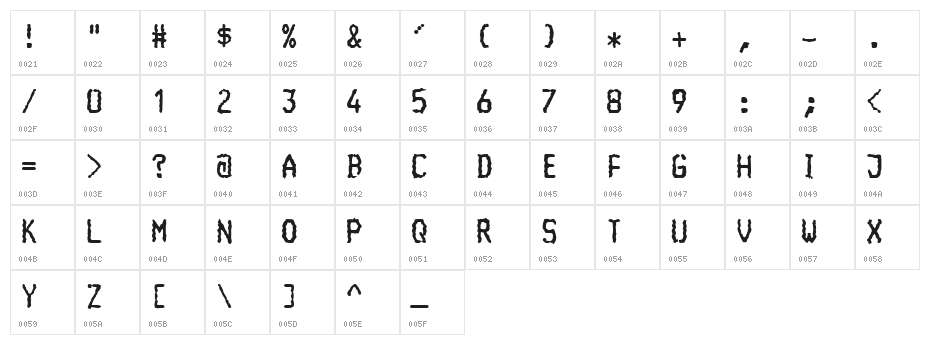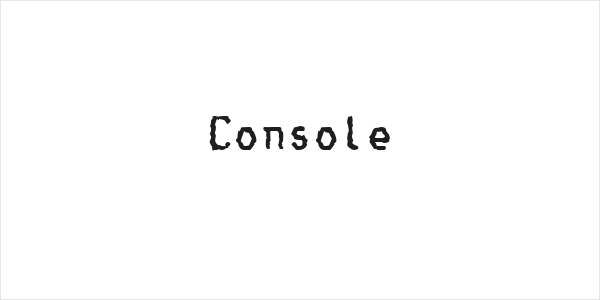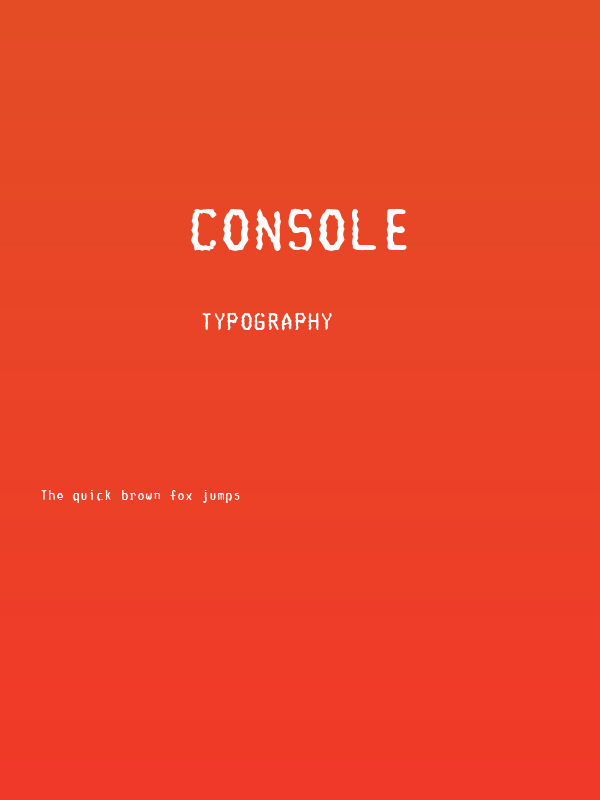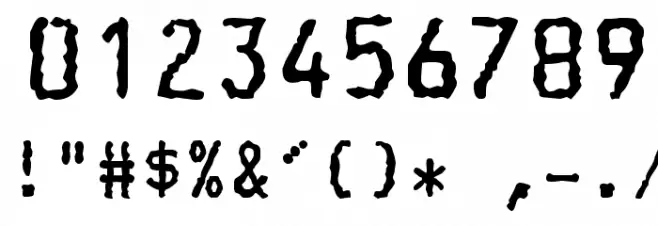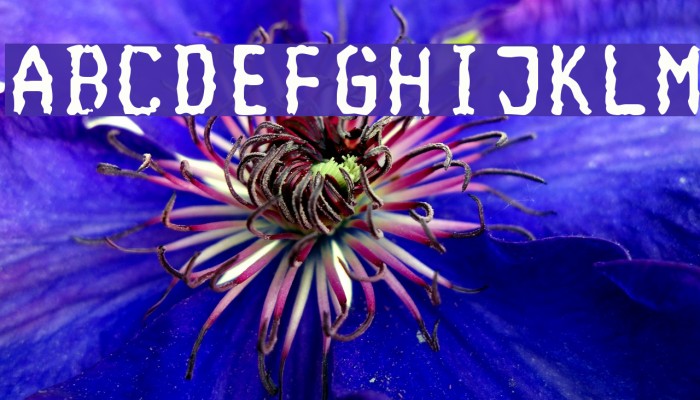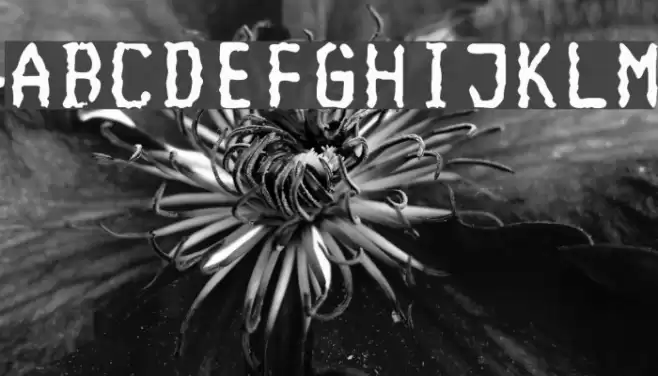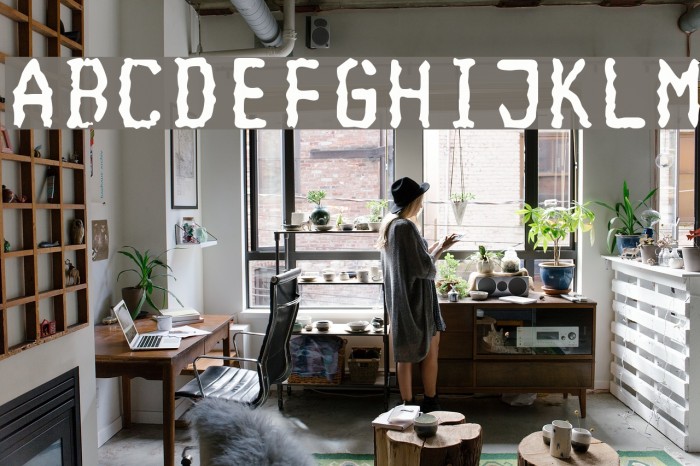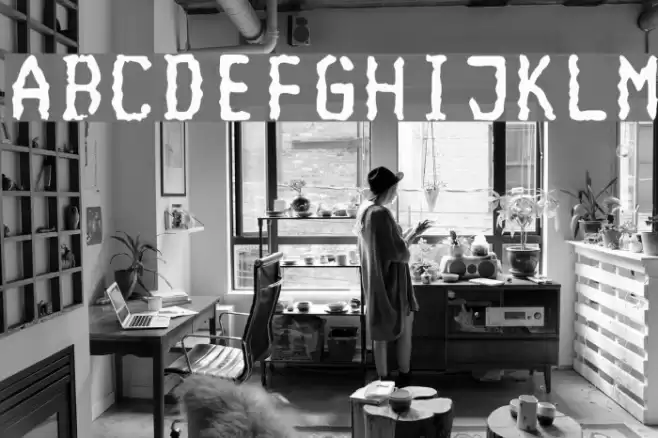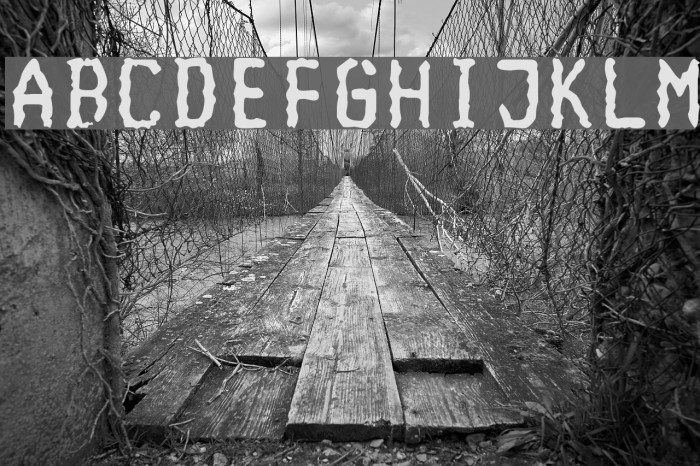
Console Font
✎ Quirky
| Nom | Console |
| Catégories | Quirky |
| Projets proposés | Ideal for posters, album covers, branding for creative industries, and any project needing a bold, artistic touch. |